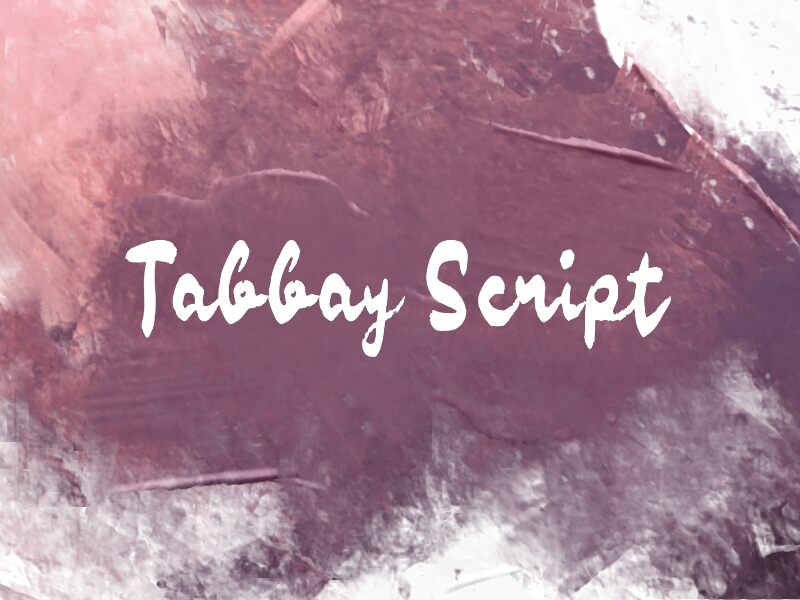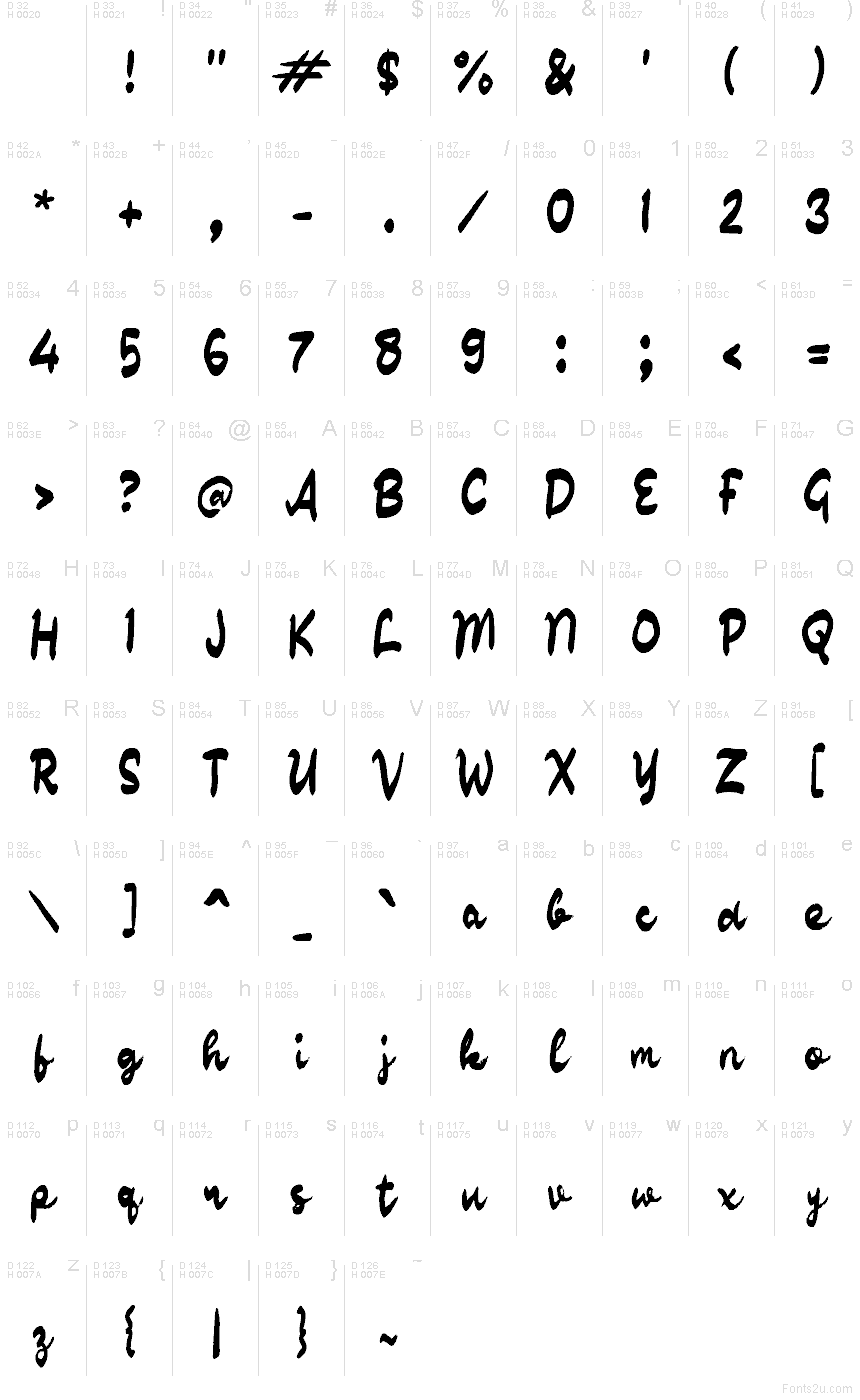
Tabbay Script от Wep — это бесплатный акцидентный шрифт (brush script), напоминающий свободный стиль рисованных вывесок, с его густыми, будто начертанными тушью штрихами. Буквы выглядят динамично и живо, с округлыми формами, высоким размашистым T и мягкими соединениями, которые создают ощущение легкого ритма.
Он идеально подойдет для брендинга кофеен, стритвир-брендов, упаковки, постеров и заголовков в соцсетях, где нужен бесплатный шрифт, который сочетает в себе небрежность и уверенный характер. Используйте его для коротких надписей, обложек или логотипов, когда хотите, чтобы текстура кисти и «прыгающая» базовая линия стали главным визуальным акцентом.
Tabbay Script
Презентация и наглядный образец шрифта Tabbay Script